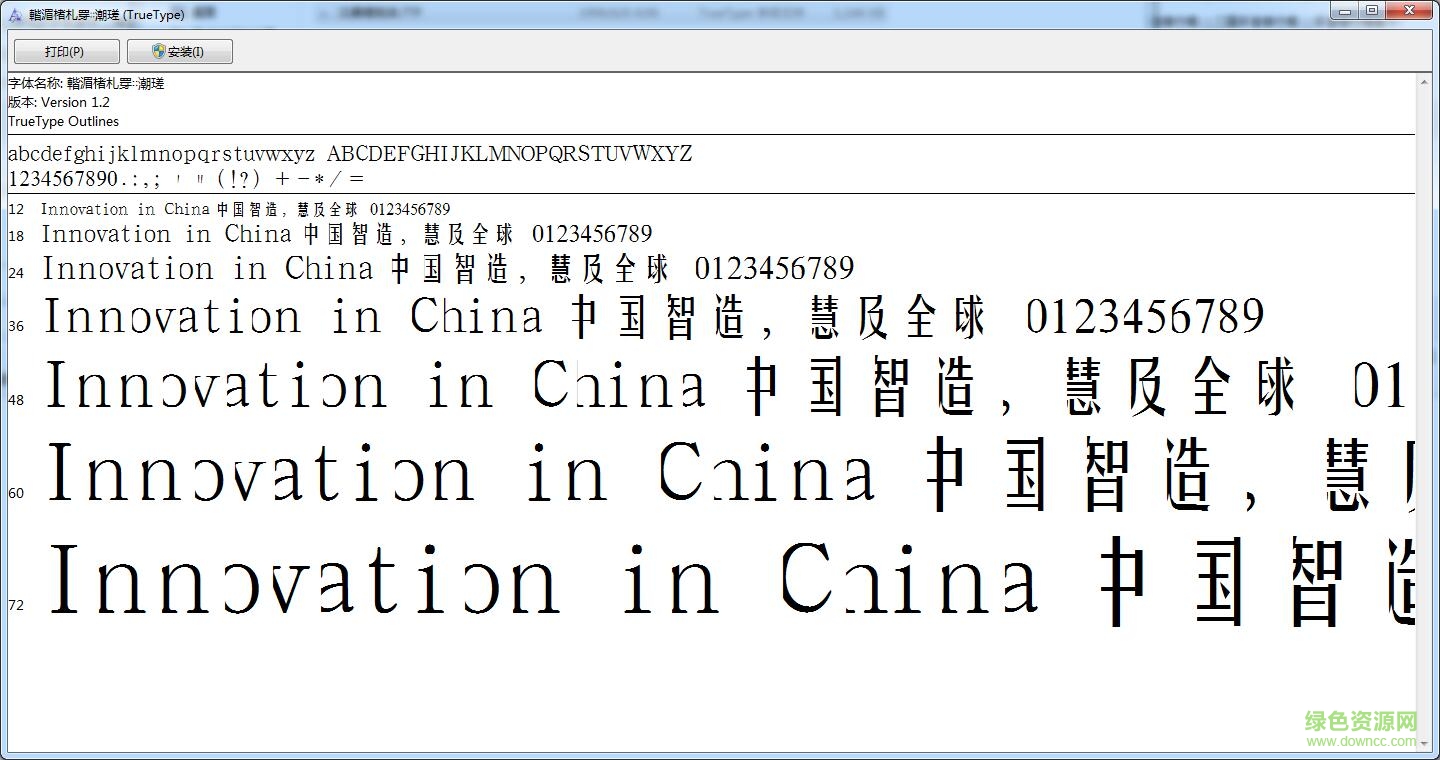
漢鼎簡姚體是一款免費的字體應(yīng)用!這款字體比較規(guī)范,字形偏長!可以在多種windows系統(tǒng)下運行安裝,其字體所表現(xiàn)的方式也比較特殊,一般很少遇見,只要專業(yè)的編輯人員才會使用,喜歡的朋友歡迎來綠色資源網(wǎng)下載。
漢鼎簡姚體是一款端正、大氣的中文簡體字體,姚體與宋體類似,不過字形更偏瘦長設(shè)計,而且字間距較大。需要商業(yè)用途的朋友要和作者聯(lián)系并取得授權(quán)。需要的用戶快來綠色資源網(wǎng)下載吧。